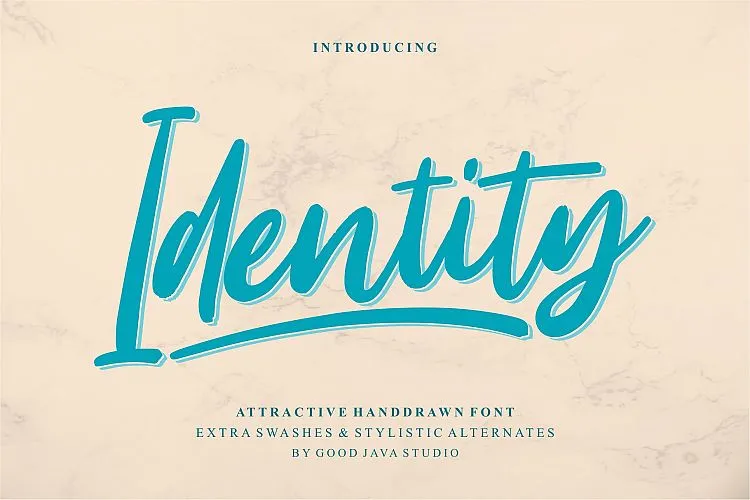
Identity Script Font – Download Grátis
A Identity Script Font é uma oferta excepcional que traz beleza e simplicidade aos seus designs digitais. Esta fonte script natural e moderna é perfeitamente adequada para diversas finalidades, incluindo logotipos, convites, embalagens de produtos, design fotográfico, até mesmo em eventos especiais. Ela foi projetada pela Good Java Studio e compartilhada com a comunidade de designers. É uma fonte escrita à mão que traz um toque elegante ao seu trabalho. Com sua graciosidade natural e estilo contemporâneo, a Identity Script Font é perfeita para adicionar uma pegada única e sofisticada aos seus projetos digitais. Seja você designer de logotipos ou criação de convites de casamento, ela oferece a oportunidade de dar um toque especial a seu design com apenas alguns cliques. Obrigado à Good Java Studio por compartilhar essa fonte maravilhosa que adiciona uma pitada única ao design digitais.